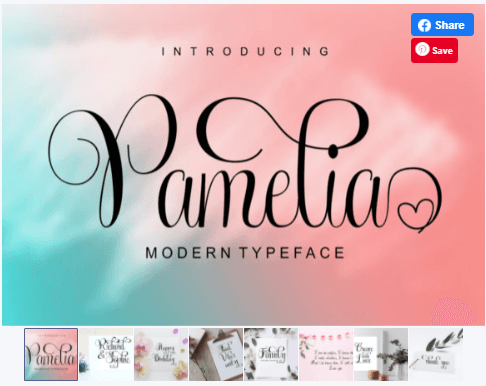
Pamelia Font
Pamelia - гладкий, изысканный шрифт. Он великолепно смотрится на приглашениях на свадьбу, открытках с благодарностью, цитатах, поздравительных открытках, логотипах, визитных карточках и любом другом дизайне, который требует индивидуального подхода. Этот шрифт имеет кодировку PUA, что означает, что вы можете легко получить доступ ко всем глифам и росчеркам!